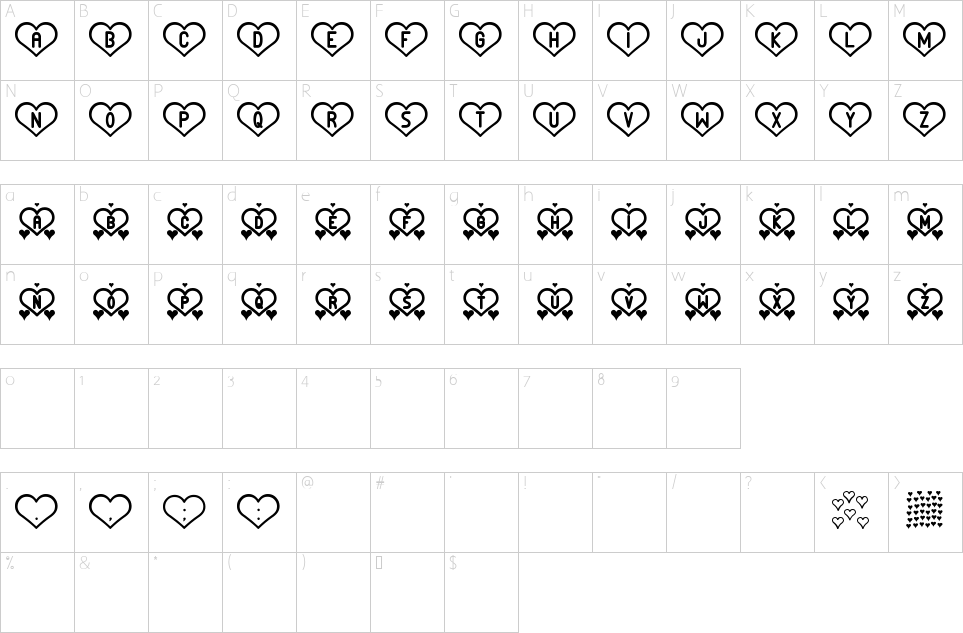
A fonte And Love St é uma escolha natural e envolvente para seus projetos de design. Desenhada por Southype, esta fonte é um charme para qualquer projeto de texto, seja para o seu site pessoal, site de negócios, aplicativo de smartphone ou até mesmo para criar cartões de visita. Se você busca um estilo moderno e elegante, And Love St é a fonte perfeita. Com uma aparência acolhedora e fácil de ler, a fonte combina bem com uma variedade de estilos, garantindo que seu design seja atraente e agradável aos olhos. Com downloads superiores a 46.000, é claro que a qualidade de And Love St não pode ser ignorada. Se você está procurando por uma fonte clássica e agradável que não comprometa a aparência de seu projeto, And Love St pode ser uma excelente escolha.